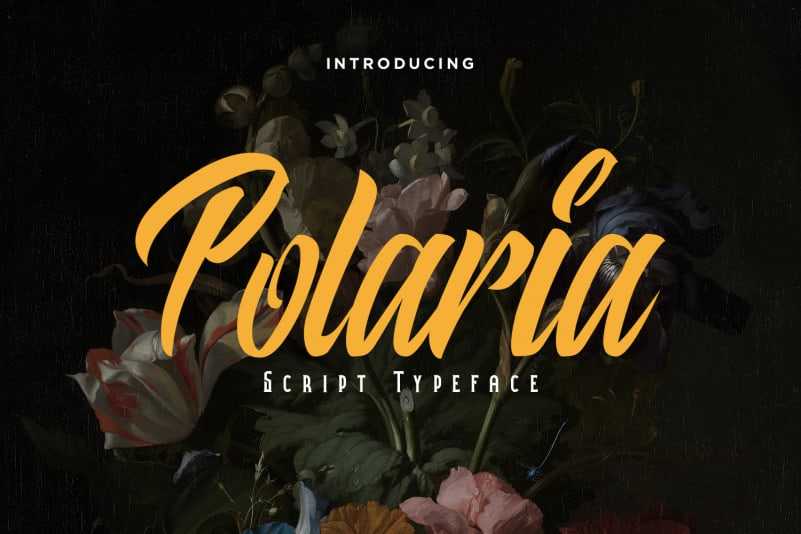
Polaria Script Typeface – Download Grátis
Polaria Script Typeface é uma fonte de tipografia moderna que combina elegância com um estilo casual perfeito para projetos criativos. Seja para criar logotipos, cartões personalizados ou embalagens, Polaria atende a todos esses requisitos e mais. Suavemente fluida, esta fonte é ideal para texturas gráficas de alto nível, desde cabeçalhos poderosos até etiquetas delicadas. A sua versatilidade não tem limite: pode usá-la em banners publicitários, desenhos a personalizar e até mesmo roupas estampadas. Sempre com um toque moderno, esta fonte é um must-have para todos os designers que buscam criar uma identidade visual única e inspiradora.